Bộ Font chữ viết tay là bộ font chữ tiếng Việt mô phỏng kiểu chữ viết tay miễn phí dành cho Windows. Với bộ font chữ tiếng Việt này bạn có thể thỏa sức sáng tạo nên các kiểu chữ đánh máy mà giống chữ viết tay để tạo nên sự gần gũi, thân thiện và cũng đầy sáng tạo. Tải bộ Font chữ viết tay ngay để thể hiện được cá tính của bạn trong các văn bản đánh máy.
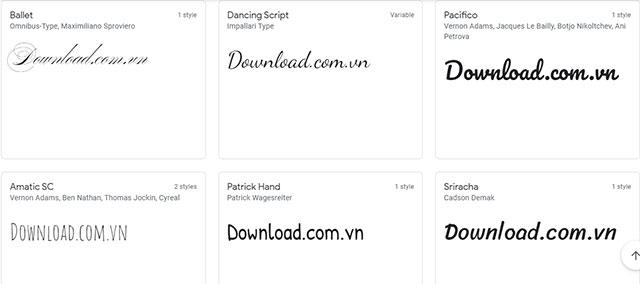
Trong Bộ Font tiếng Việt đầy đủ cũng có một số mẫu chữ viết tay, tuy nhiên với Bộ Font chữ viết tay bạn sẽ thỏa mãn lựa chọn mẫu chữ bạn yêu thích. Chúng ta sẽ sáng tạo để tạo khi đánh máy, đặc biệt với các thầy cô giáo thì đây là font chữ vô cùng cần thiết để viết mẫu cho học sinh.
Yếu tố sáng tạo luôn được đánh giá rất cao trong lĩnh vực thiết kế, chính điều đó đã kích thích họ luôn tìm tòi những điều mới. Thay vì những font chữ quá đơn giản, quen thuộc thì Bộ font chữ viết tay lại mang đến rất nhiều cảm hứng, không đặc biệt như Font chữ thư pháp nhưng font chữ viết tay sẽ mang đến được rất nhiều thiện cảm của người dùng.
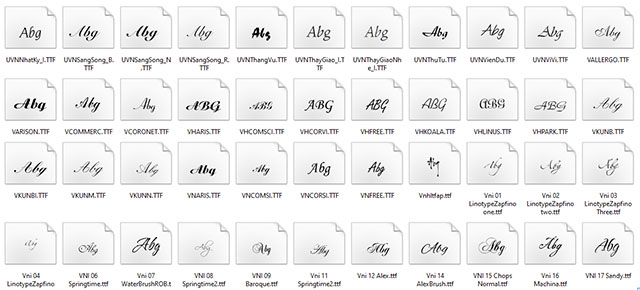
Ngoài ra Google cũng thiết kế riêng cho tiếng Việt một bộ font chữ tiếng Việt vô cùng đơn giản, mang dáng dấp của Font chữ Google Sans mà bạn không thể bỏ qua. 14 định dạng khác nhau với nét chữ viết tay uyển chuyển sẽ nhanh chóng chinh phục các độc giả.
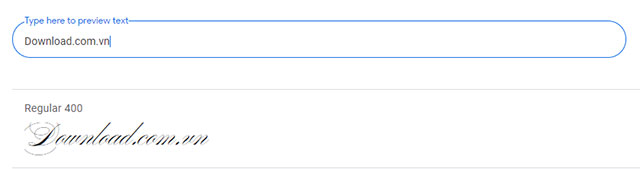
Các nét chữ viết tay luôn khiến người nhìn bị cuốn hút, tất cả các font chữ trong Bộ font chữ viết tay đều có sự đặc biệt riêng. Chúng ta sẽ thỏa sức sáng tạo nên các bản vẽ, bản thiết kế để tạo nên điểm nhấn cá nhân.